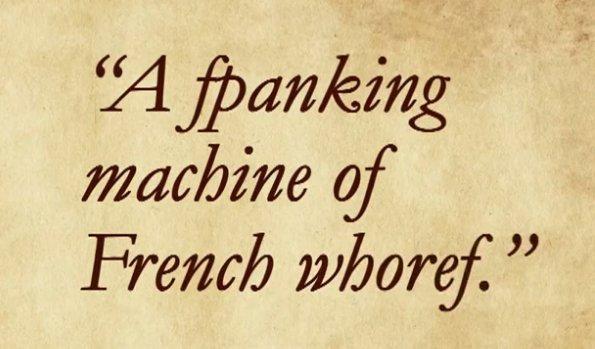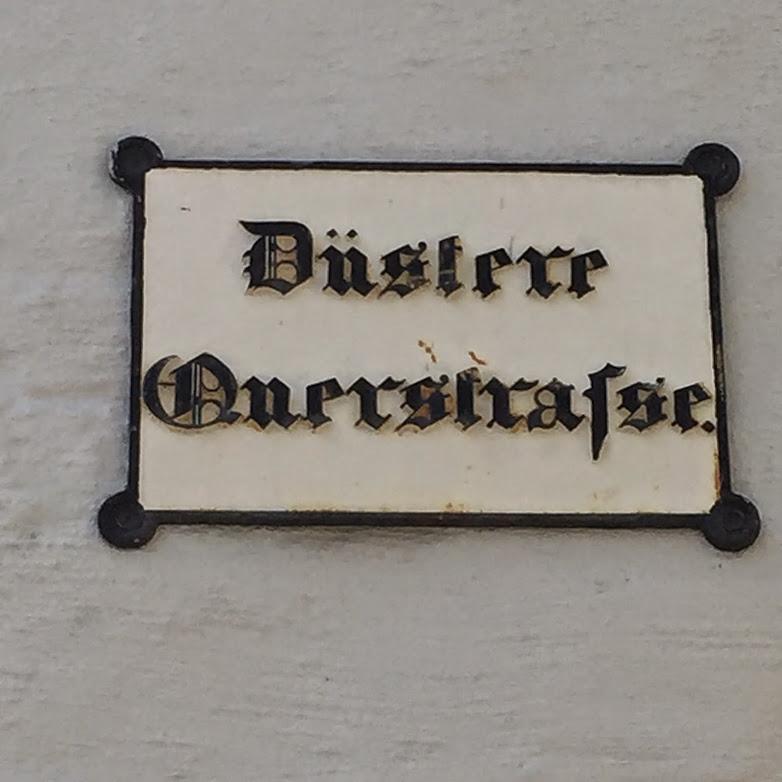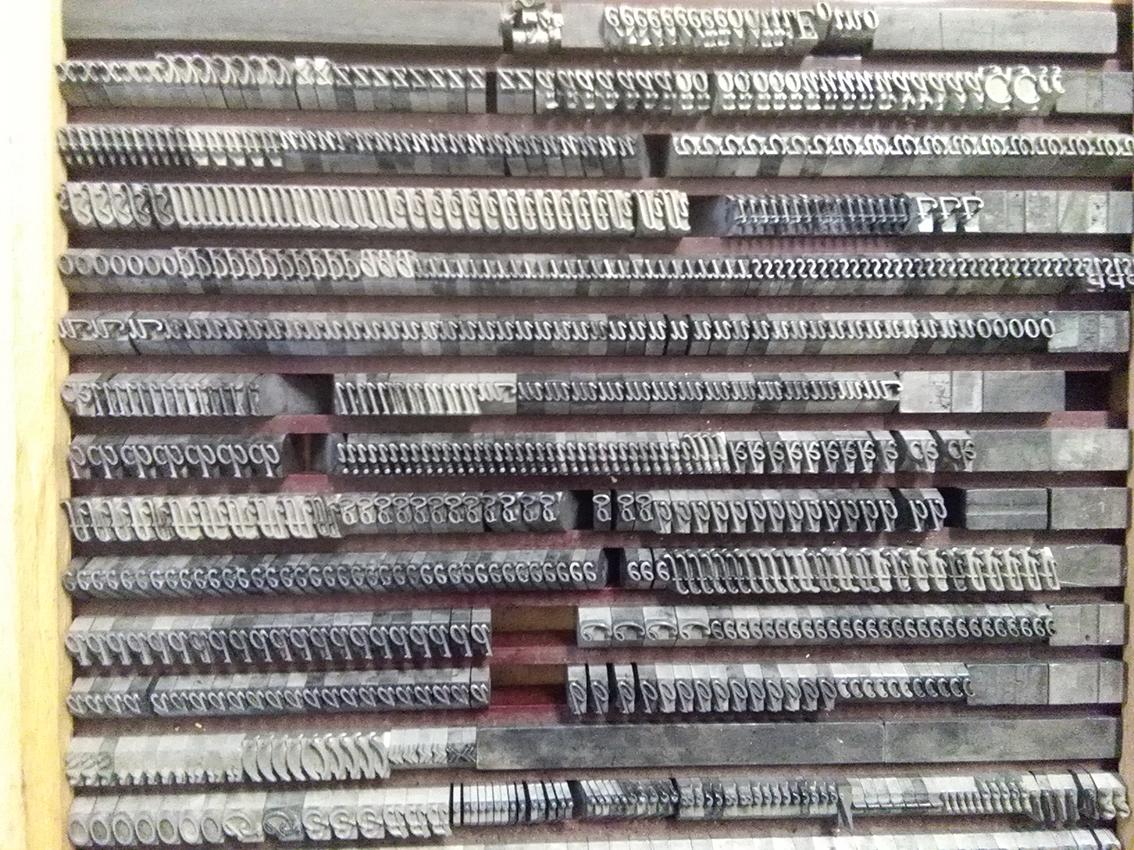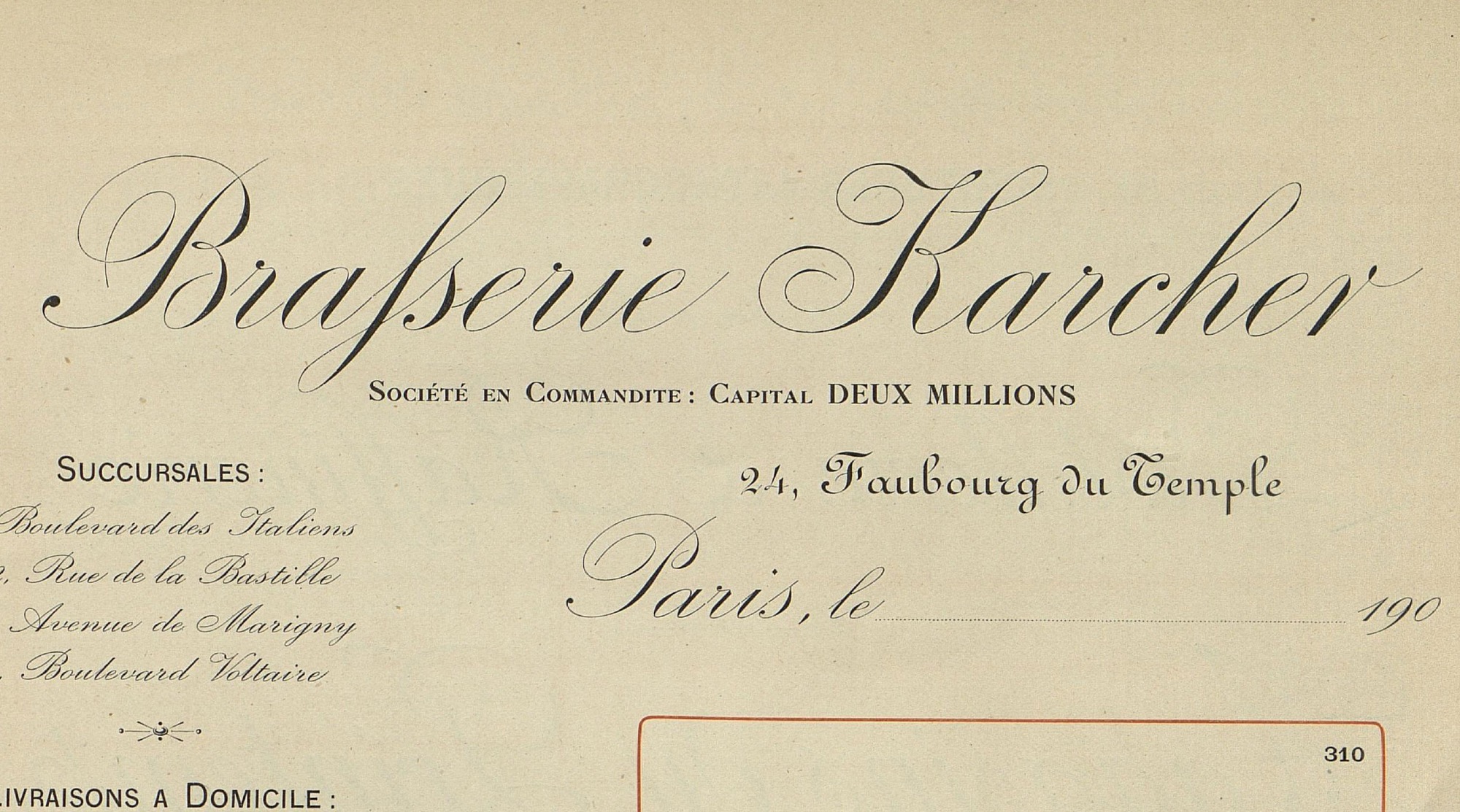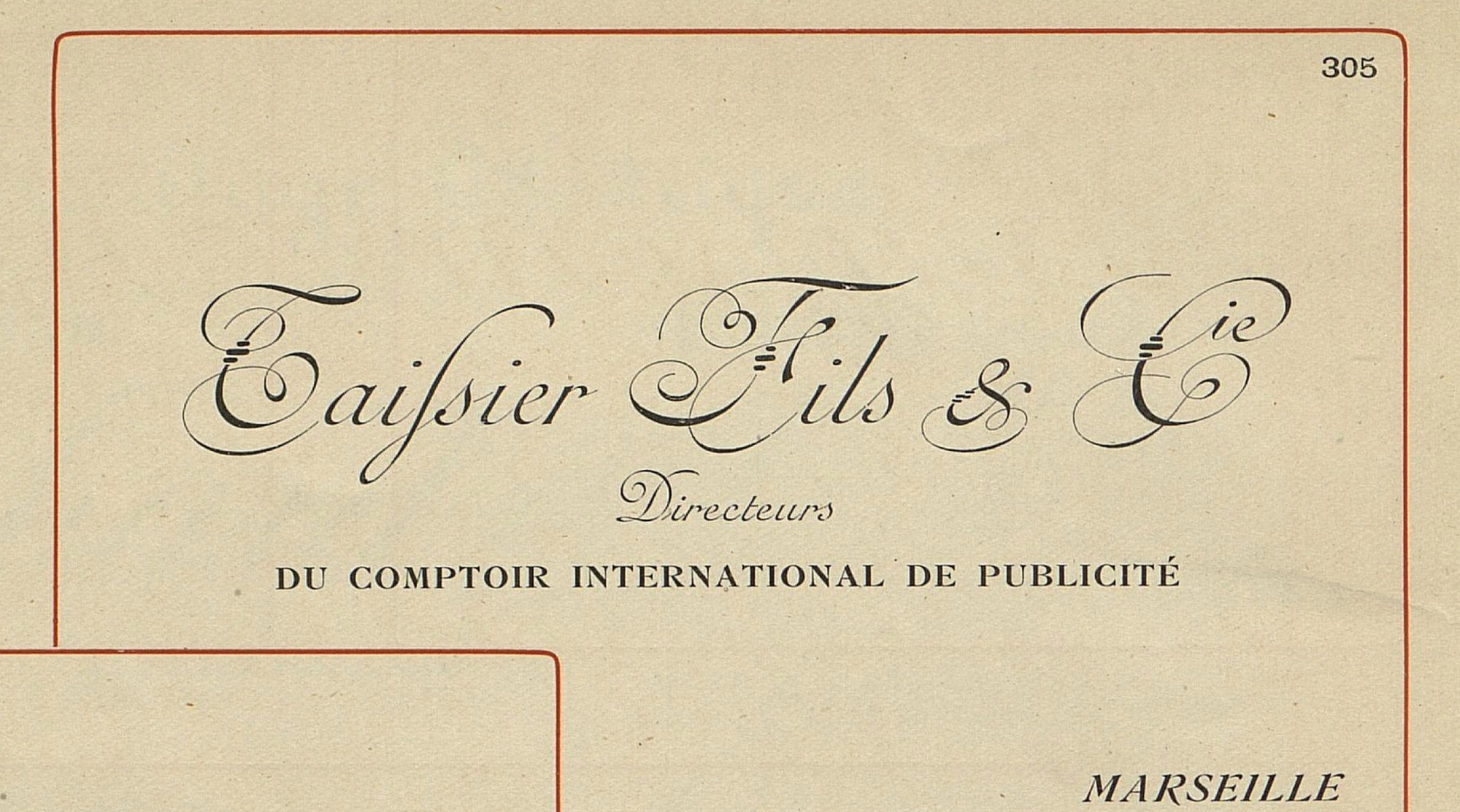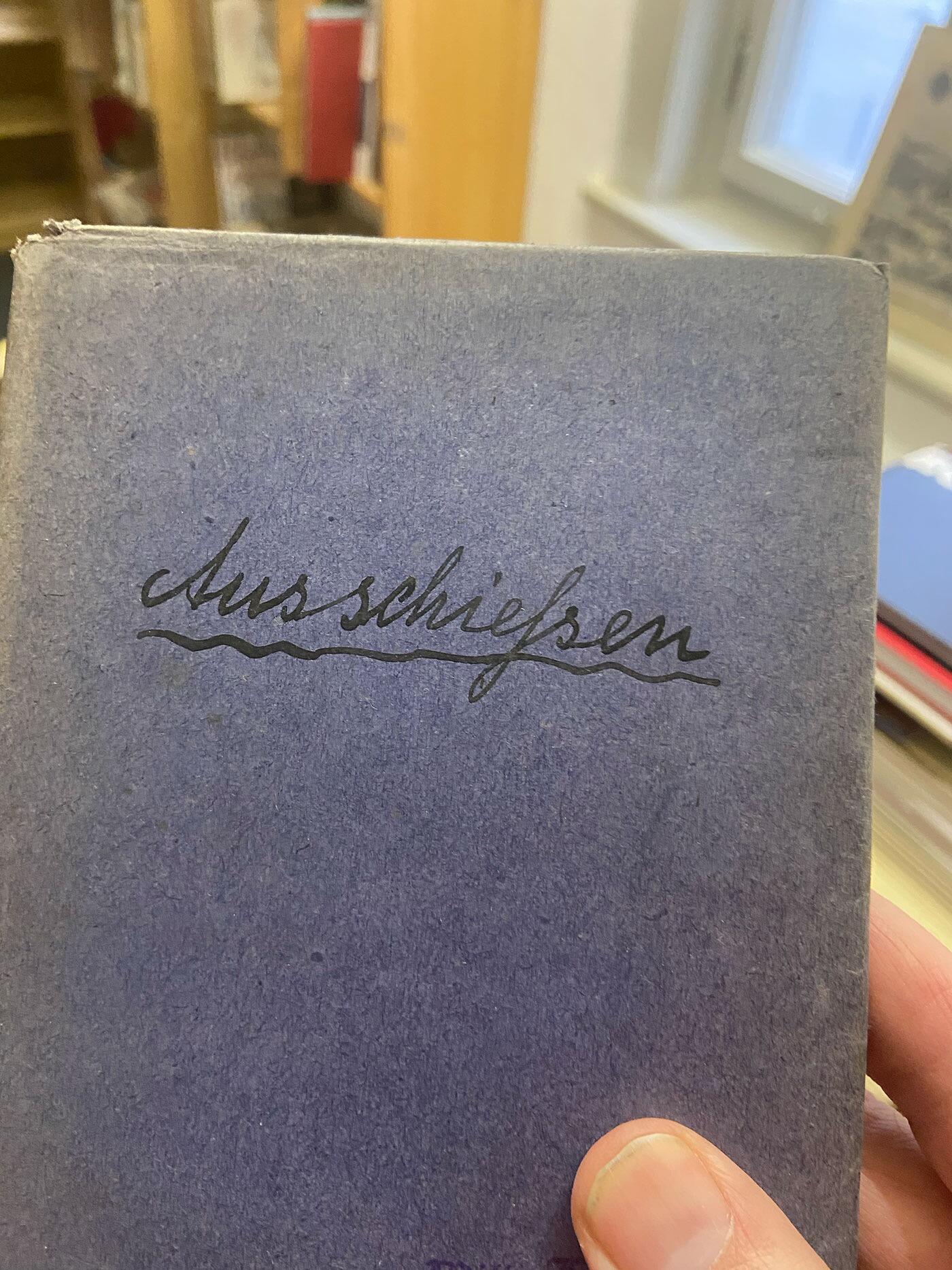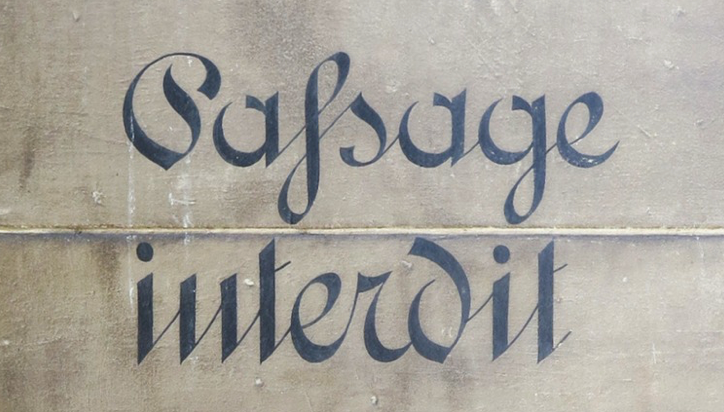
Hier ein weiteres Beispiel einer Schreibschrift aus der Walbaum’schen Gießerei
Was für ein schönes Griechisch! das Zeta ist ja unglaublich sexy :)
In meiner Jugendzeit begegnete mir auch mal so eine  Schreibweise. Wandte mich deshalb an einen  mir bekannten Schriftsetzer.
Sein Kommentar: " Du siehst hier einen weiteren Beweis der  These, daß nichts Bestand  hat, außer dem Wandel".  Da das Schreiben
lange Zeit als Kunst betrachtet worden sei, hätten sich auch die "Künstler" mitunter solche "Freiheiten" erlaubt. Eine Normung oder
verbindliche  Regelung des Schriftgebrauches, wie z. B.  bei Duden, gab es noch nicht. Solche "Künstler"  waren oft " bei Hofe" fest
angestellt, da die Herren selbst oft der"Kunst" nicht mächtig waren. So gesehen könne man da wohl mitunter auch von  weidlich
genutzter "Narrenfreiheit" sprechen. Im oben gezeigten Fall war ich auch sofort beim  h aus der Kurrent. Aber Irren ist ja bekanntlich menschlich. Also " Mensch bleiben! Woll?"
In meiner Druckwerkstatt befindet sich eine Garamond kursiv die noch mehr dieser für mich rätselhaften Ligaturen hat, nicht nur ſs oder sſ, sondern auch ſſ, ſſs oder ſt. Weiß jemand in welchen Fall diese Ligaturen evt. heute noch eingesetzt werden können? Siehe Steckkasten-Belegung Foto anbei. Kasten_Garamond_kursiv.jpg.1dcb5498172ae3eb5560769aa8f79862.jpg
nicht nur ſs oder sſ,
sſ habe ich im Buchdruck noch nie gesehen. Sicher, dass das irgendwo da im Bild zu sehen sein soll?
sondern auch ſſ, ſſs oder ſt. Weiß jemand in welchen Fall diese Ligaturen evt. heute noch eingesetzt werden können?
Das ist für deutsche Bleisatzschriften bis in die erste Hälfte des 20. Jahrhunderts völlig normal. Zwar war das lange s offiziell mit der alten deutschen Rechtschreibung aus der Antiqua abgeschafft worden, aber in Buchdruckerkreisen hielt es sich noch eine Weile. Nicht auf breiter Front, aber es blieb eben weiter in der Zeichenbelegung der Schriftgießereien.
Da wo heute noch die alte Satzweise des Bleisatzes benutzt wird, nimmt man dann ja gern auch noch die alten Rechtschreibregeln und Satzkonventionen. In Buchdruck-Workshops weise ich z.B. stets auf die alten Satzweisen hin und die Teilnehmer können dann selbst entscheiden, ob sie ein langes s benutzen wollen oder nicht. Das wird meist ganz pragmatisch entschieden, etwa im Hinblick darauf wer die Drucksachen später in die Hände bekommt und wie gut diese Zielgruppe das lesen kann.
sſ habe ich im Buchdruck noch nie gesehen. Sicher, dass das irgendwo da im Bild zu sehen sein soll?
Wenn ich das Bild ſpiegel, ſehe ich auch nur ſs, ſ, ſſ, ſi, ſt, ſſi als Ligaturen.
nicht nur ſs oder sſ, sondern auch ſſ, ſſs oder ſt.
sſ hat es meines wissens nie als Ligatur gegeben, ist ja auch nicht wirklich sinnvoll,, da diese ja kein Satzproblem löst, ſs hingegen gab es, als Alternative zu ß, eben für worte die auf ss enden, für ein besseres Kerning zwischem ſ und s allerdings ist  ſs zumindest in diesem Kasten nicht drin.
Die Ligaturen ſi, ſj, ſh, ſk, ſl, ſſ, ſt sowie einige 3er-Ligaturen wie ſſi, ſſl, ſſk und ſſt sind sehr wohl sinnvoll, besonders im Fraktursatz, da hier ein ſ gefolgt von einem hoch aufragenden Buchstaben, sogar noch schlimmer als beim f eine hässliche Lücke im Satz reißen würde.
Die Ligaturen sorgen so für die notwendige Unterschneidung.
Die von mir erwähnten Ligaturen sind daher auch fester Bestandteil von vollständig ausgebauten digitalen Frakturschriften
die Ligatur sſ gibt's tatsächlich nicht im Schriftkasten, das war ein Fehler von mir. Aber danke für die Info betr. der anderen Ligaturen, ich werde es dann wie vorgeschlagen
In Buchdruck-Workshops weise ich z.B. stets auf die alten Satzweisen hin und die Teilnehmer können dann selbst entscheiden, ob sie ein langes s benutzen wollen oder nicht.
einsetzen.
Nun. zumindeſt hätte es bei der Verwendung von ſ und s hier dieses Problem kaum gegeben:
Und ſo greife ich zu einem röſchen Weihnachtskeks, und ſinge: "es ist ein Ros' entsprungen...
Womit sich der Kreis zu ſs wieder schließt. Denn der erzürnte MDR-Hörer besteht ja klar auf einem Rös·ſchen·hof. :-P
Denn der erzürnte MDR-Hörer besteht ja klar auf einem Rös·ſchen·hof. :-P
Aber eben über eine Fuge hinweg, daher doch keine Ligatur, oder?
Ob Ligaturen (durch ihre Abwesenheit) Wortfugen kennzeichnen sollten, haben wir ja schon oft kontrovers diskutiert. (Ich denke nicht.)
Aber bei sſ wäre das sowie irrelevant. Da gibt es gar keine plausible Ligaturmöglichkeit, oder?
Wobei sie es verbockt haben: das “lange s” hier ist ja nur ein f, und dann noch am Wortende gesetzt...
Die Regel, dass Ligaturen nicht über Fugengrenzen gesetzt werden sollen, führt aber manchmal zu sehr unschönen Schriftbildern. Es gibt einen Verlag (Diogenes?), bei dem ich häufiger über Wörter wie »Auf lage« stolper. Da ist der Abstand zwischen f und l fast genauso groß, wie in den zwei Wörtern »Straff liegt …«. Natürlich hängt das auch mit der verwendeten Schrift zusammen. Ist der Bogen des f sehr großzügig, dann lässt sich sowas kaum verhindert. Gut, wenn die Schrift dann ein alternatives f mit schmalem Bogen hat.